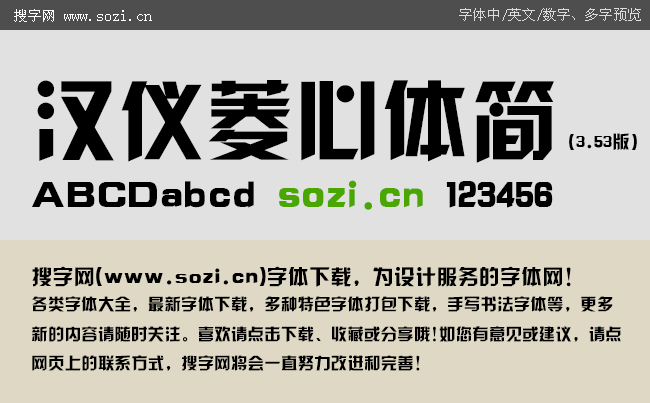
漢儀菱心體簡3.53版
搜字網(wǎng)提供一款漢儀菱心體簡中文藝術(shù)字體下載,漢儀菱心體簡是一款筆畫粗壯、新穎獨(dú)特的藝術(shù)字體,該字體具有醒目、突出的視覺效果,適用于包裝印刷、廣告設(shè)計(jì)、平面設(shè)計(jì)、海報(bào)設(shè)計(jì)等領(lǐng)域。
- 風(fēng)格類別: 海報(bào)POP體